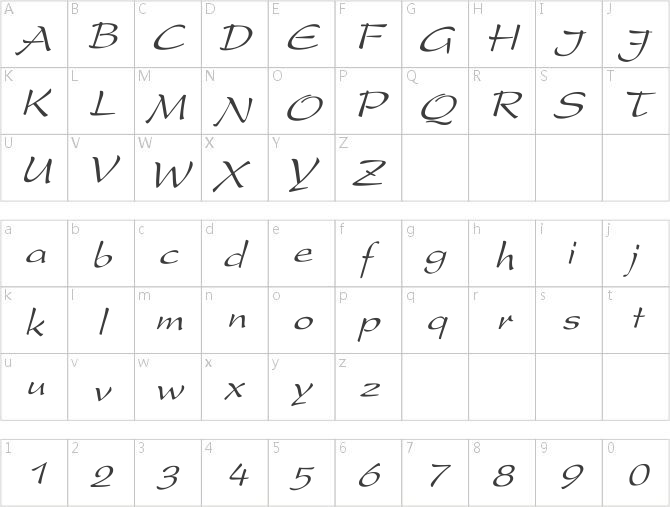
字體名稱: Present
Present-Italic
Present-Italic字體字庫是一款讓人賞心悅目、百看不厭的英文字體,適合各類廣告和產(chǎn)品包裝設(shè)計(jì)應(yīng)用,字體大小0.13MB,格式為ttf字體,上傳用戶是華大文化傳媒,作者/版權(quán)方為未知